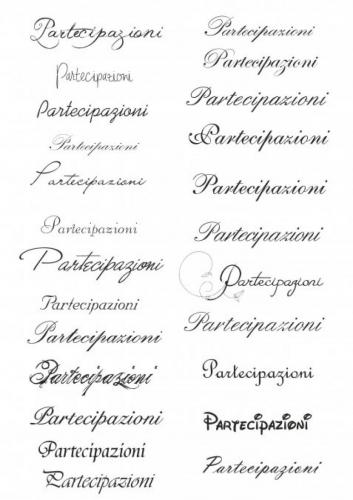
Font Per Partecipazioni Matrimonio
In passato abbiamo già affrontato diverse volte il tema delle partecipazioni di nozze, parlando di stili, misure e formati, ecc.Se state, tuttavia, pensando di creare inviti di nozze fai da te o desiderate personalizzare il tipo di carattere sulle vostre partecipazioni di matrimonio, vi comunico che il trucco sta tutto nel trovare il font giusto!.
Infatti ogni font ha una sua personalità e va utilizzata nel modo e nello spazio corretto poiché i suoi piccoli dettagli fanno sì che esprimano. Bauer, Bodoni, Roman) e i Sans Serif Font, i caratteri senza le grazie, chiamati comunemente bastoni (es:. I font si dividono in due grandi categorie:.
Non mancano i caratteri più romantici, che danno un tocco da favola al lieto evento:. Anche la scelta dei fonts (il tipo di carattere) è importante per la buona riuscita estetica delle tue partecipazioni matrimonio fai da te. Oggi voglio parlare dei font delle partecipazioni di matrimonio… Cosa sono?.
I font sono le tipologie di carattere grafico che dovrete scegliere per realizzare le vostre partecipazioni di nozze. Dieci font gratuiti per inviti, menu e molto altro. Esistono veramente un’infinità di font da poter scegliere per le proprie partecipazioni e capisco che si possa andare in confusione abbastanza facilmente, per questo affidarsi a un professionista grafico vi darà una sicurezza in più su quelle che sono le scelte migliori per il vostro matrimonio.
Ne esistono di infiniti, ma è bene seguire i suggerimenti dei grafici più esperti nel mondo del wedding e selezionare solo quelli ideali in base al tema nuziale (che ad esempio può essere un colore come il matrimonio a tema giallo) e alla leggibilità. Sono i caratteri usati per scrivere. Per le partecipazioni che spedirai, ti consiglio di scrivere a mano le buste, ma se proprio non hai una bella calligrafia, allora stampale utilizzando il secondo font della coppia scelta.